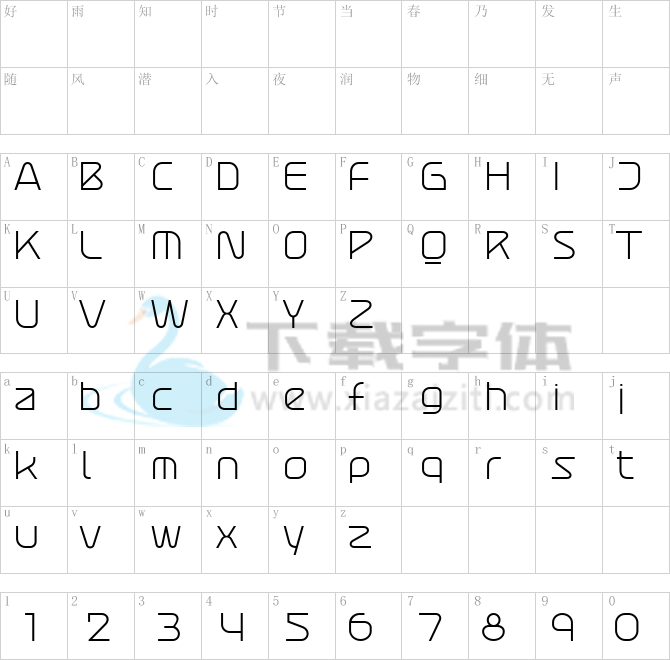
Atures 300 PERSONAL USE ONLY.ttf字体下载
Atures 300 PERSONAL USE ONLY.ttf字体下载,这款字体结构工整、笔画清晰,兼顾美观与易读性,适用于标题、正文、海报、包装、LOGO 等多种场景。字形优雅稳定,风格百搭耐看,适配日常排版与创意设计,让文字呈现更舒适、更具质感。Atures 300 PERSONAL USE ONLY.ttf字体下载一笔一画,皆是细节,以均衡的比例、流畅的线条打造舒适视觉体验,字形端正大气,风格简约现代。无论是商业设计、品牌宣传还是日常排版,都能轻松驾驭,让文字更有格调与力量。Atures 300 PERSONAL USE ONLY.ttf字体下载字体下载。